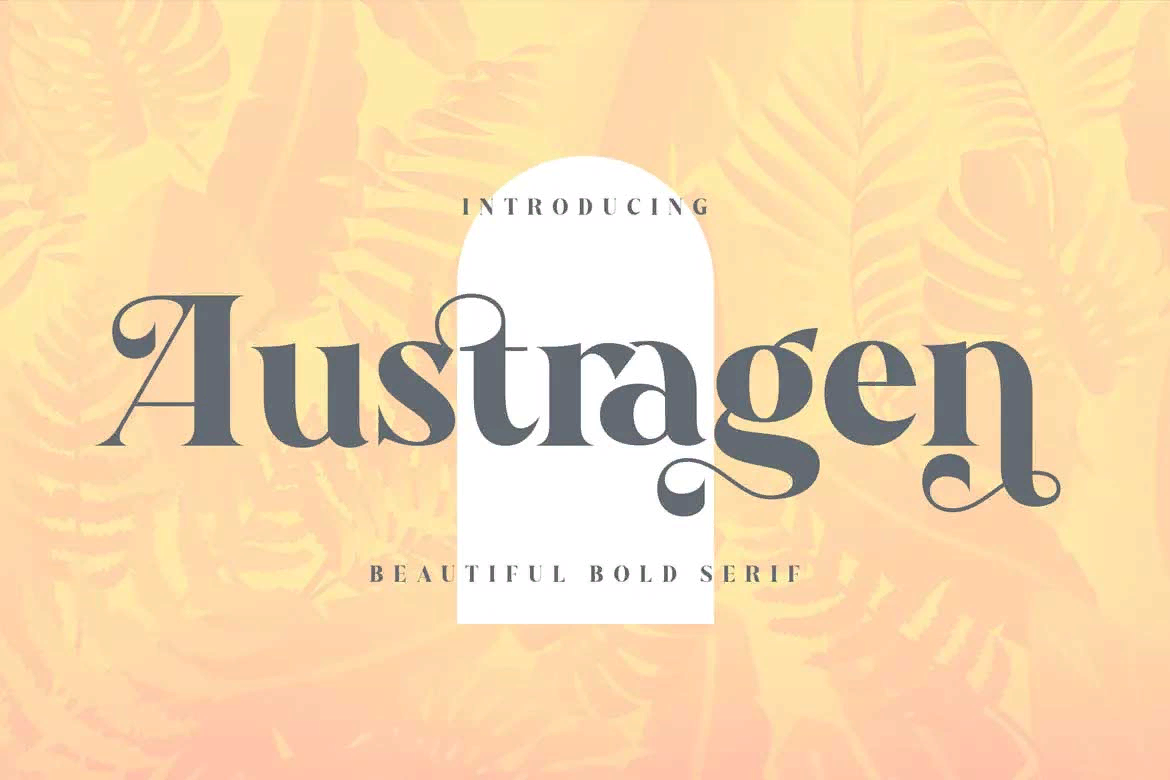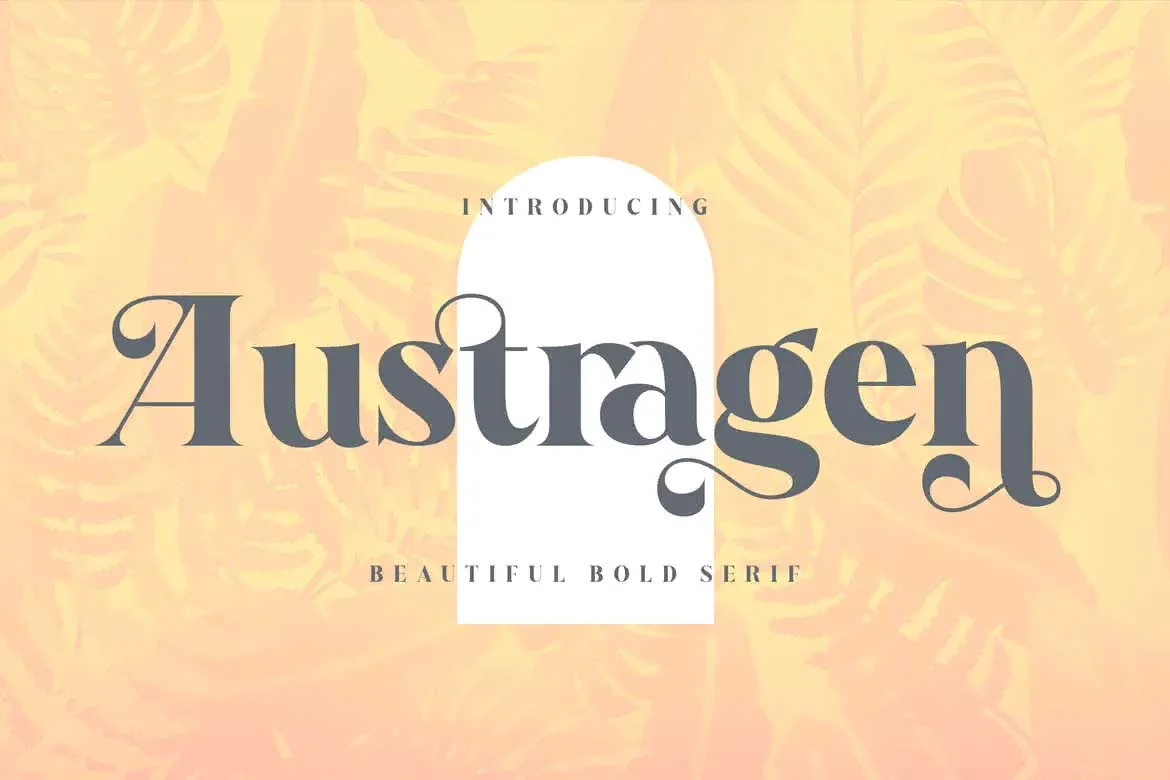
Название: Austragen Font (2021)
Austragen - это модный и смелый шрифт с засечками.
Он имеет стильный вид, который можно использовать для логотипов, брендинга, приглашений, канцелярских принадлежностей, свадебных дизайнов, постов в социальных сетях и многого другого!